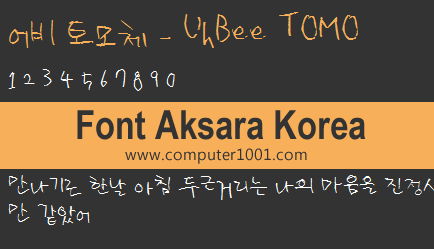
Anda bisa mendapatkan berbagai bentuk font aksara Korea seperti goresan kuas ataupun tulisan tangan yang cute, untuk digunakan pada desain poster, banner, atau gambar yang ingin ditaruh di Tumblr, postingan di blog serta forum untuk penggemar K-Pop / K-Drama.
Cool Text memiliki 24 font aksara Korea dengan berbagai bentuk, baik yang formal, tulisan tangan yang halus dan cantik, ataupun berbentuk goresan kuas.
Google memiliki koleksi font aksara Korea, baik yang bentuknya formal maupun yang bergaya tulis tangan.